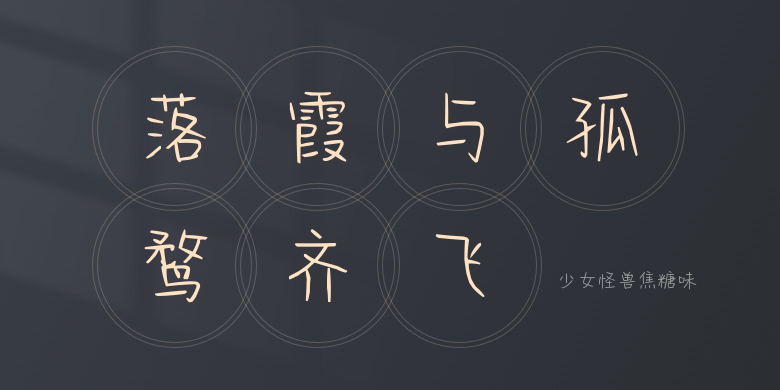
少女怪兽焦糖味
少女怪兽焦糖味,这款字体结构工整、笔画清晰,兼顾美观与易读性,适用于标题、正文、海报、包装、LOGO 等多种场景。字形优雅稳定,风格百搭耐看,适配日常排版与创意设计,让文字呈现更舒适、更具质感。少女怪兽焦糖味一笔一画,皆是细节,以均衡的比例、流畅的线条打造舒适视觉体验,字形端正大气,风格简约现代。无论是商业设计、品牌宣传还是日常排版,都能轻松驾驭,让文字更有格调与力量。少女怪兽焦糖味字体下载。